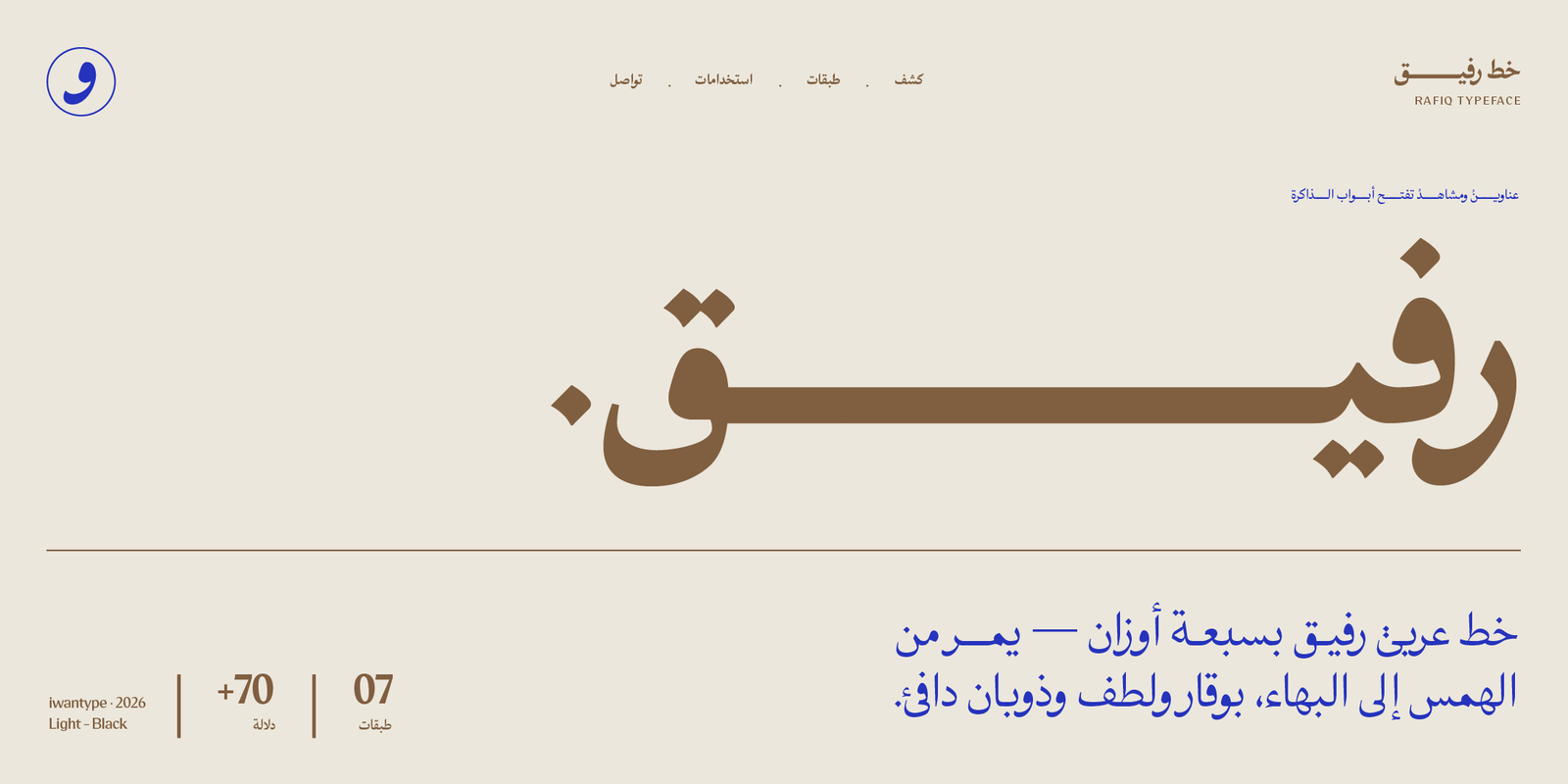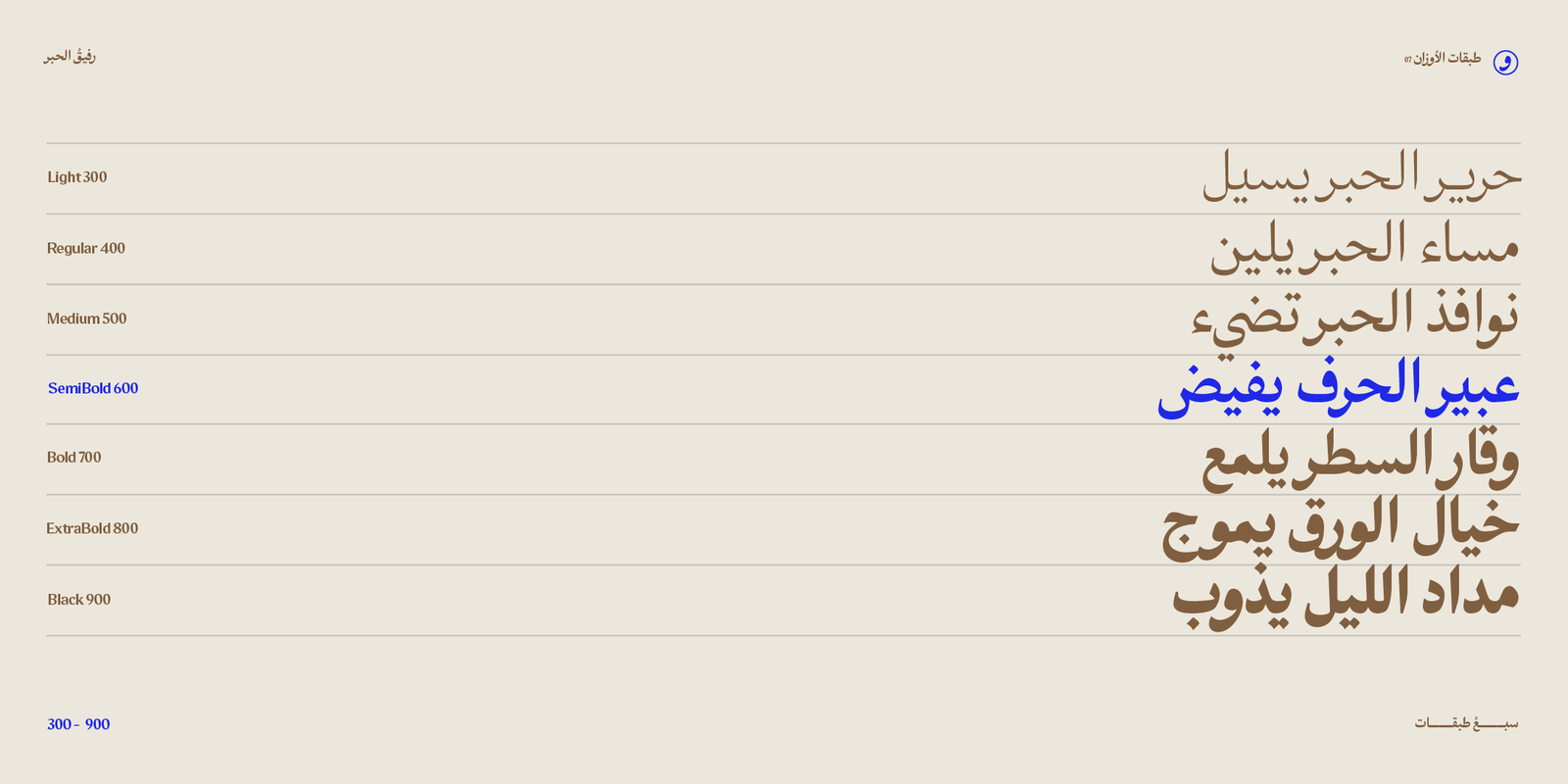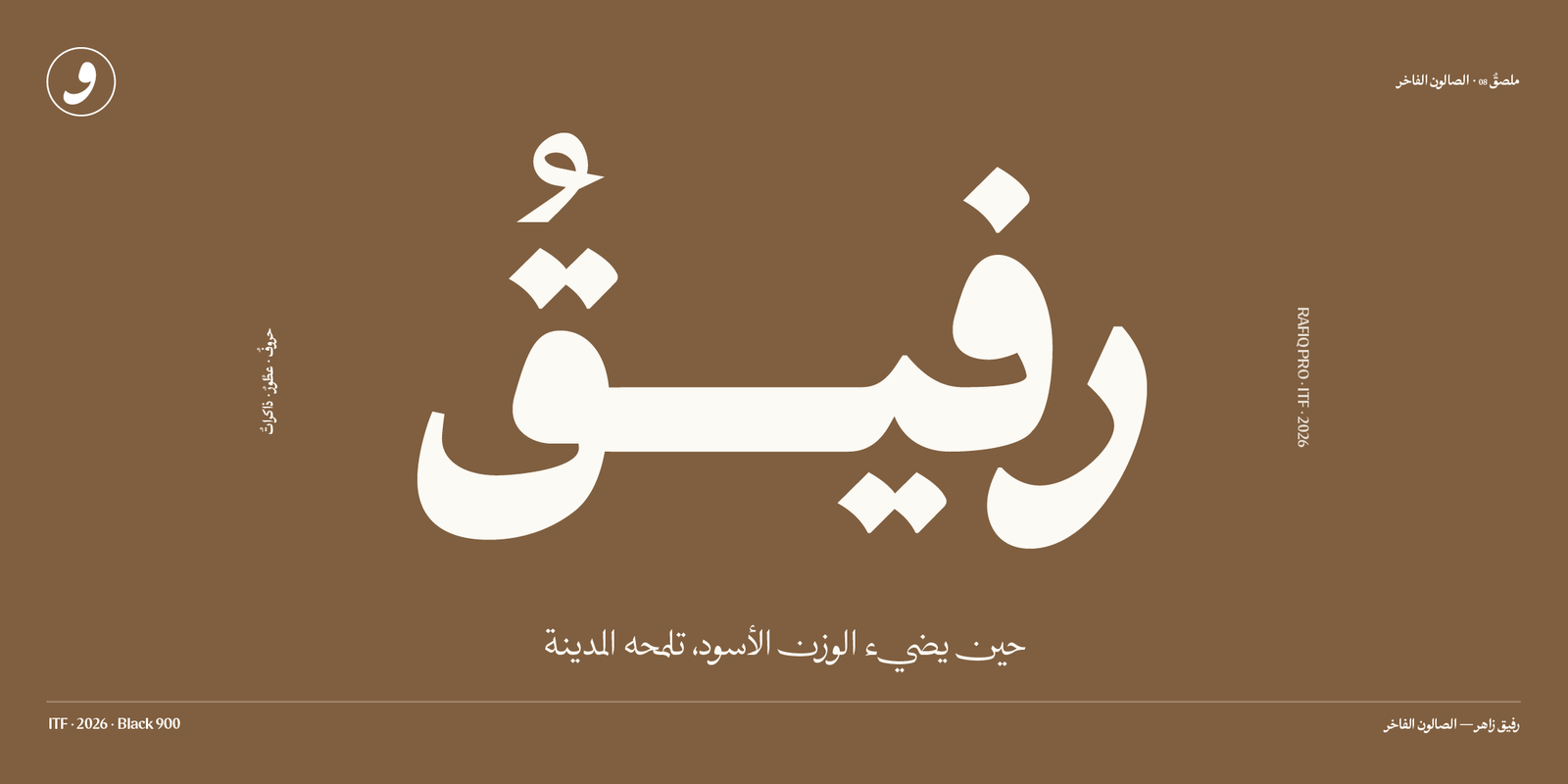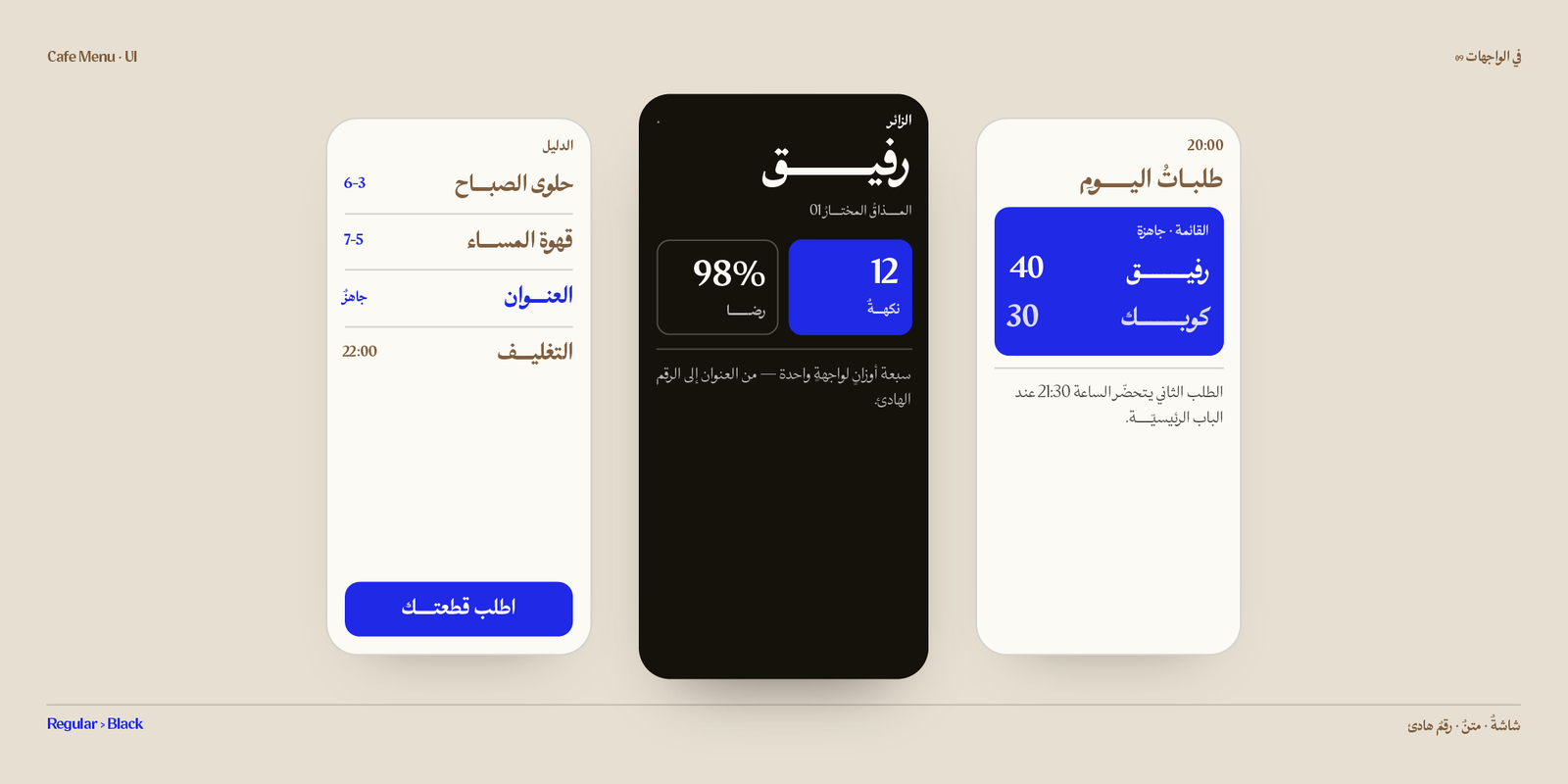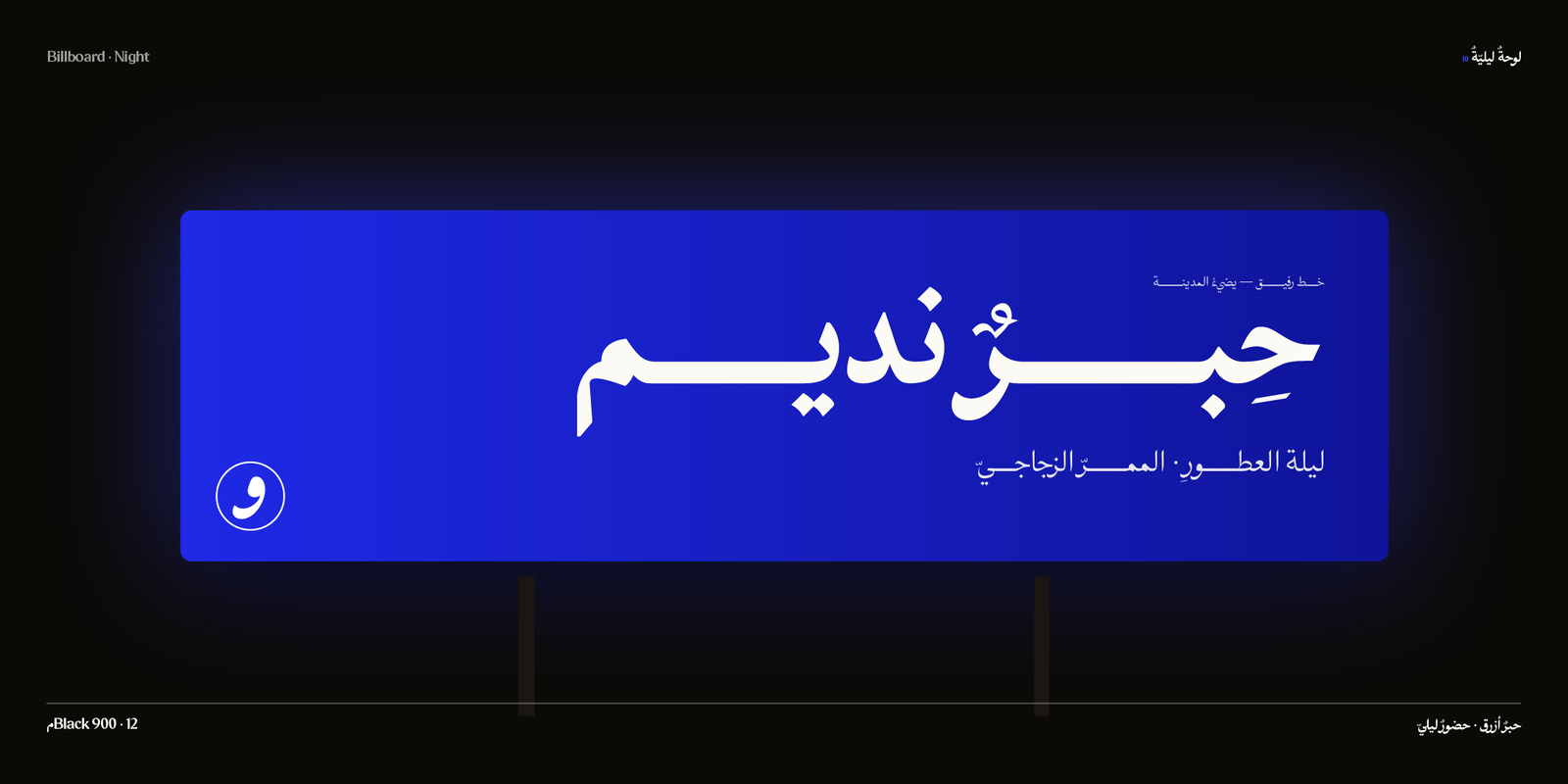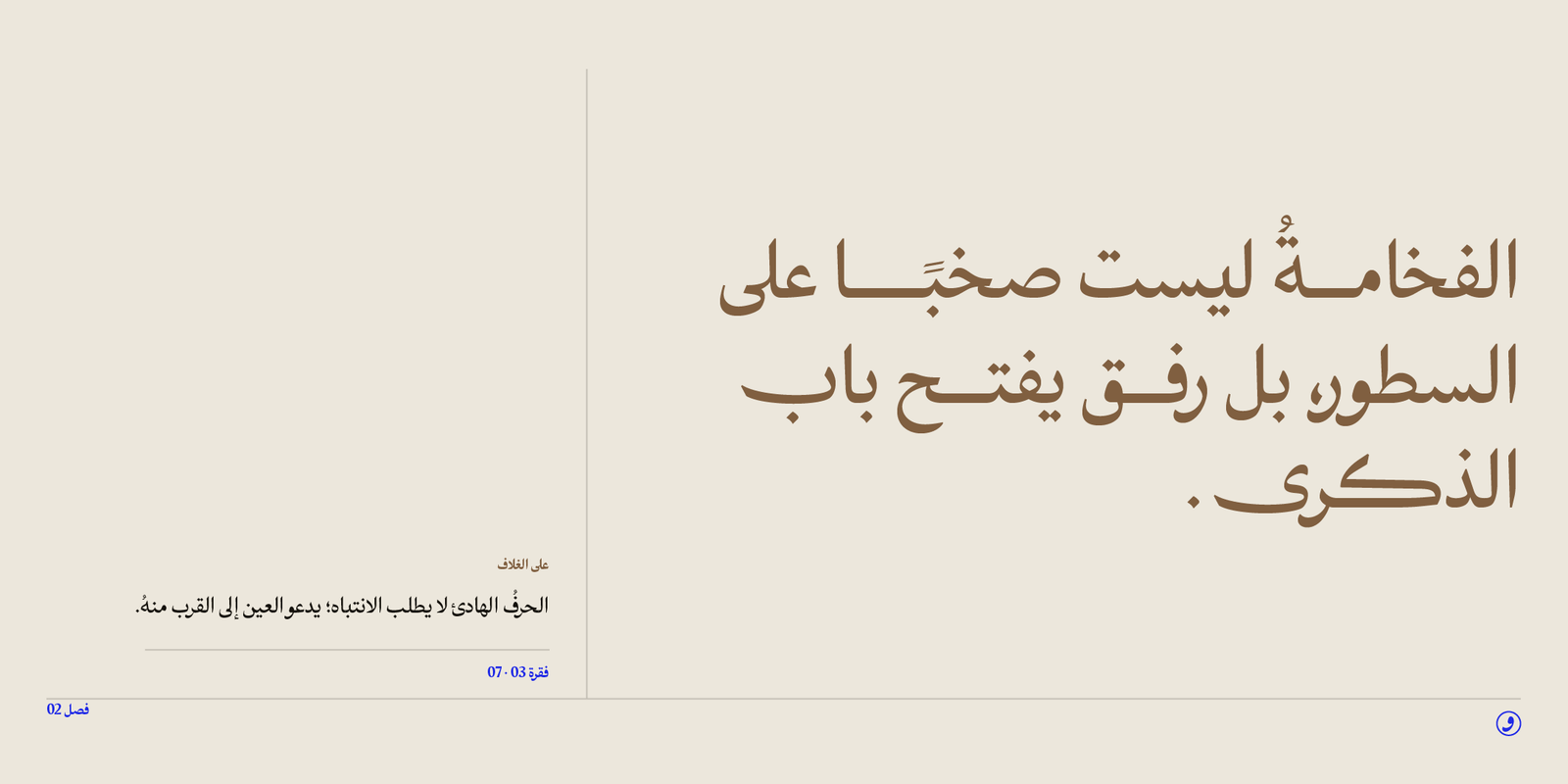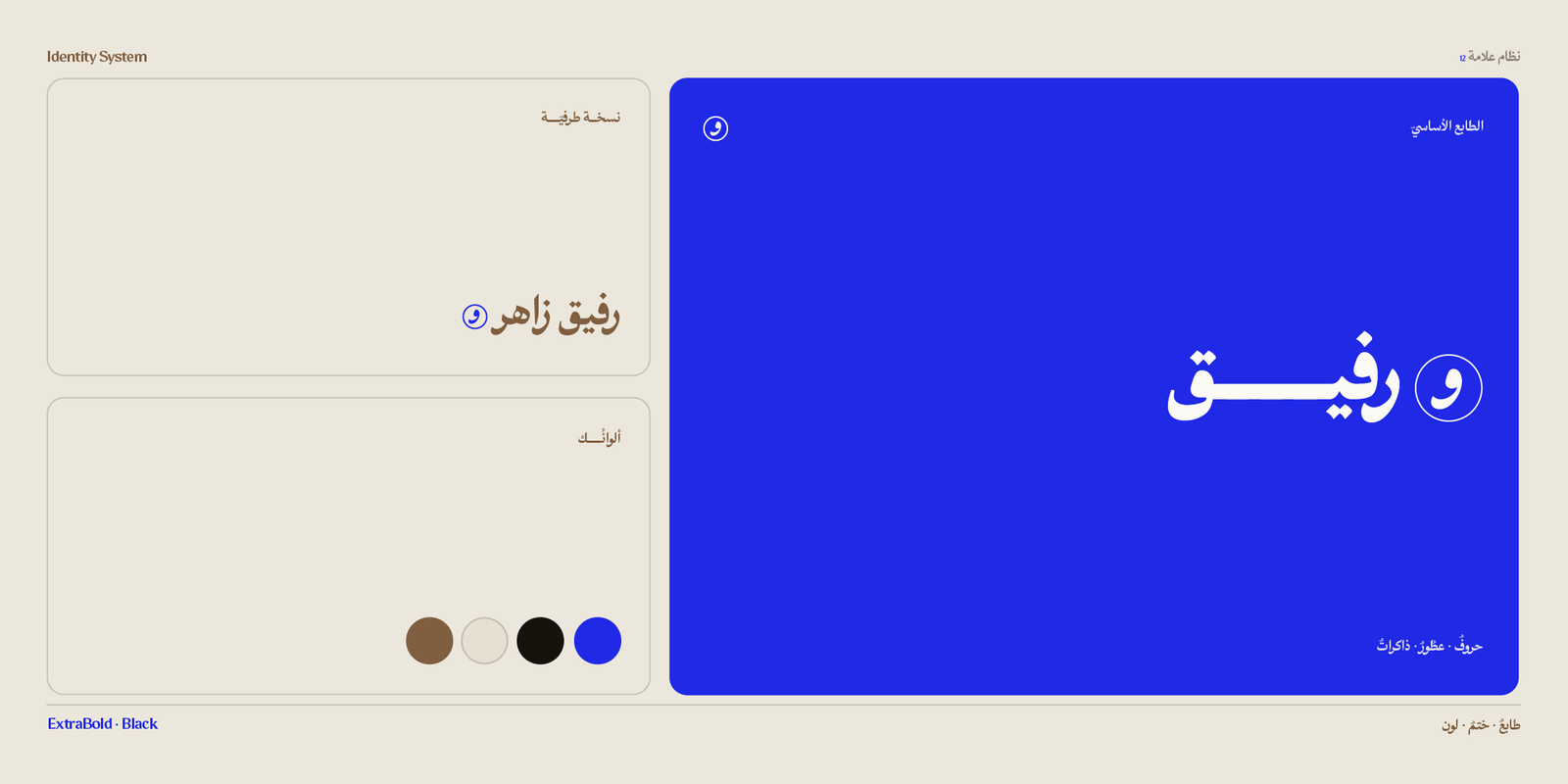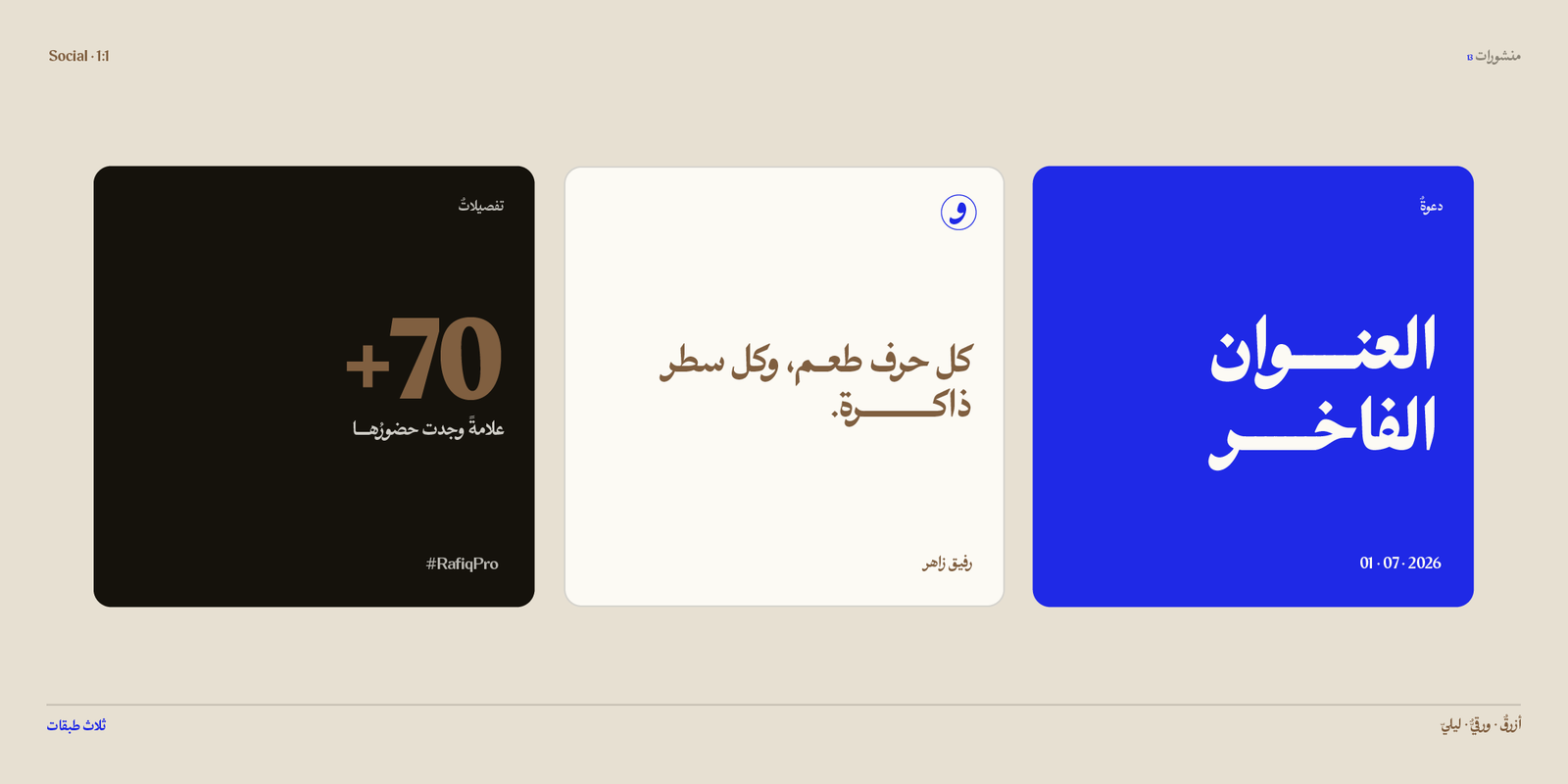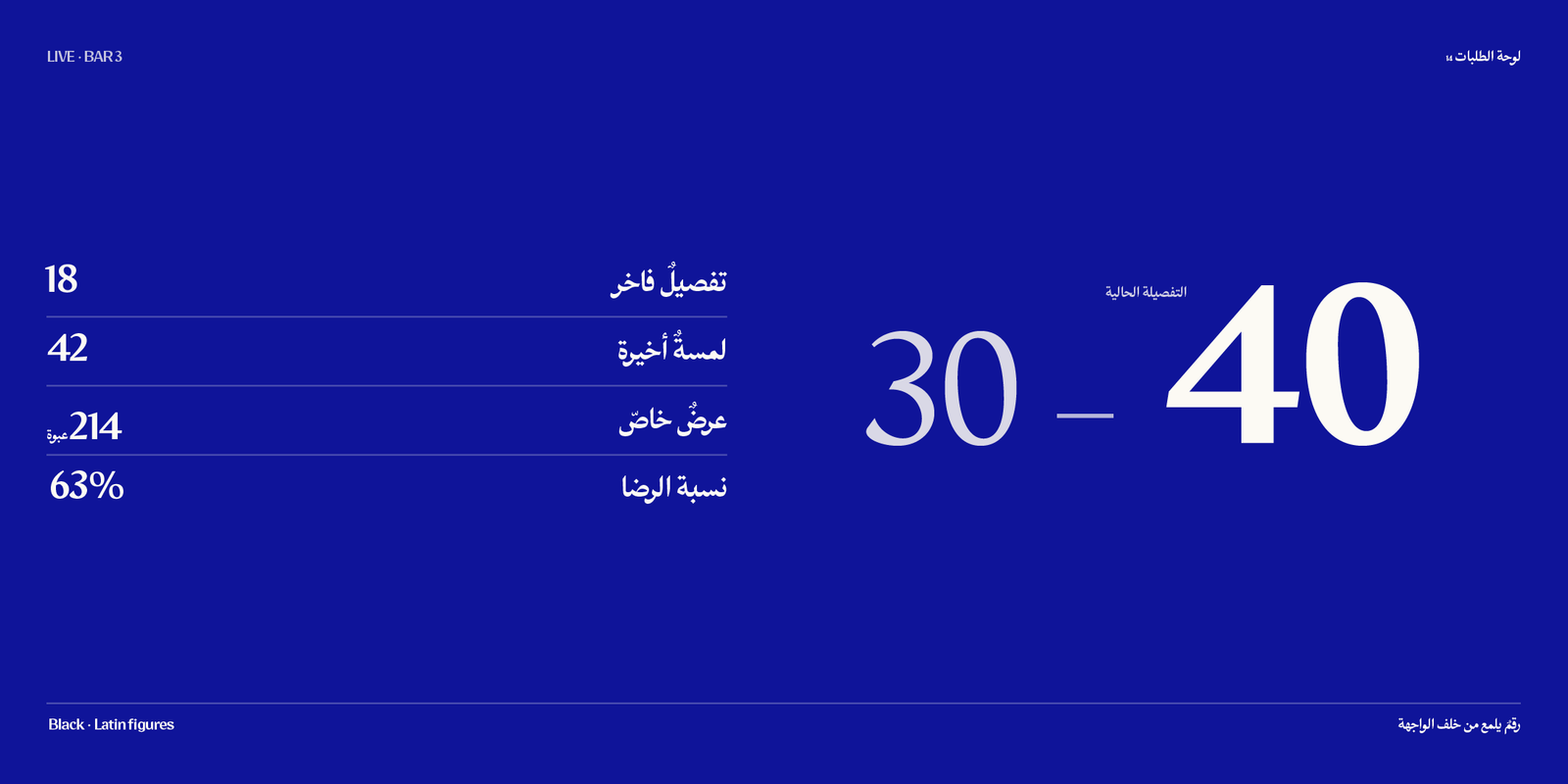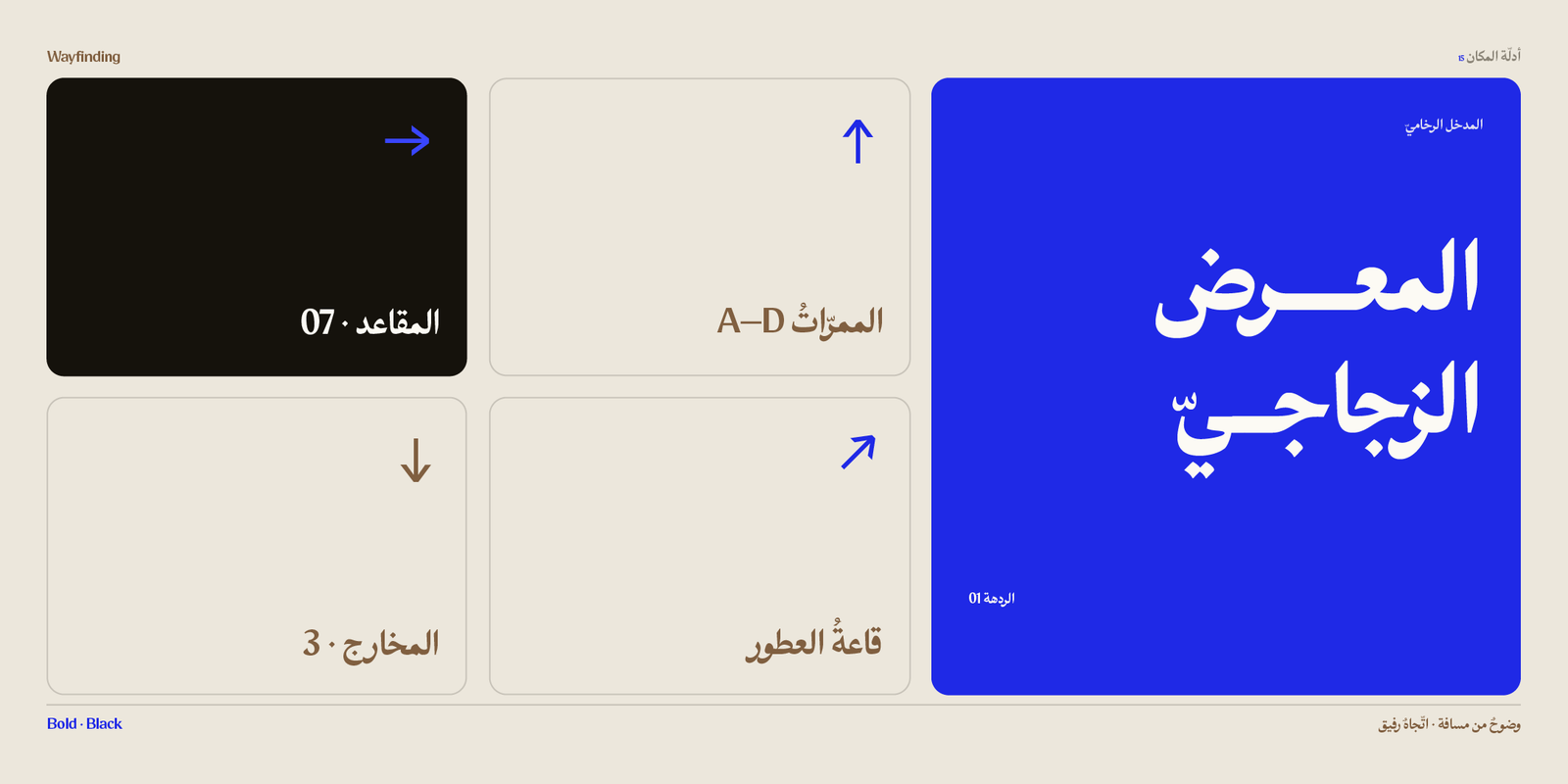
خط رفيق الطباعي – Rafiq typeface – خط نسخ عربي
خط عربي نسخي معاصر من إيوان تايب، صُمم ليكون قريبًا من العين، حاضرًا في العنوان، ومريحًا في المساحات الطويلة. يحمل رفيق روحًا هادئة في تفاصيله، وانسيابًا متوازنًا في حروفه، ليمنح التصميم نبرة راقية من دون تكلّف.
تظهر شخصية رفيق في انتقالاته اللطيفة، وفي نهاياته المهذّبة، وفي توازن المساحات الداخلية بين الحروف. هو خط يترك أثره بهدوء؛ لا يرفع صوته، لكنه يصنع حضورًا يصعب تجاهله.
مميزات خط رفيق:
يتضمن الخط العديد من مزايا OpenType التي تضفي عليه مرونة وتنوعًا في الاستخدام، مثل:
- أحرف مرسلة (تُفعَّل بإضافة “ءء” بعد الحرف)
- حرف ياء بنزول أقل: يقلل من نزول السطر، مما يعزز من انتظام النصوص.
- أحرف المركبة: تسهم في تحسين المظهر العام للنص وتزيد من سلاسته.
- نقاط بديلة
- يدعم رمز الريال السعودي، ويمكن تفعيله بإضافة حرف “ء” بعد كتابة كلمة “ريال”.
اللغات: العربية والانجليزية
الاوزان : ٧ اوزان